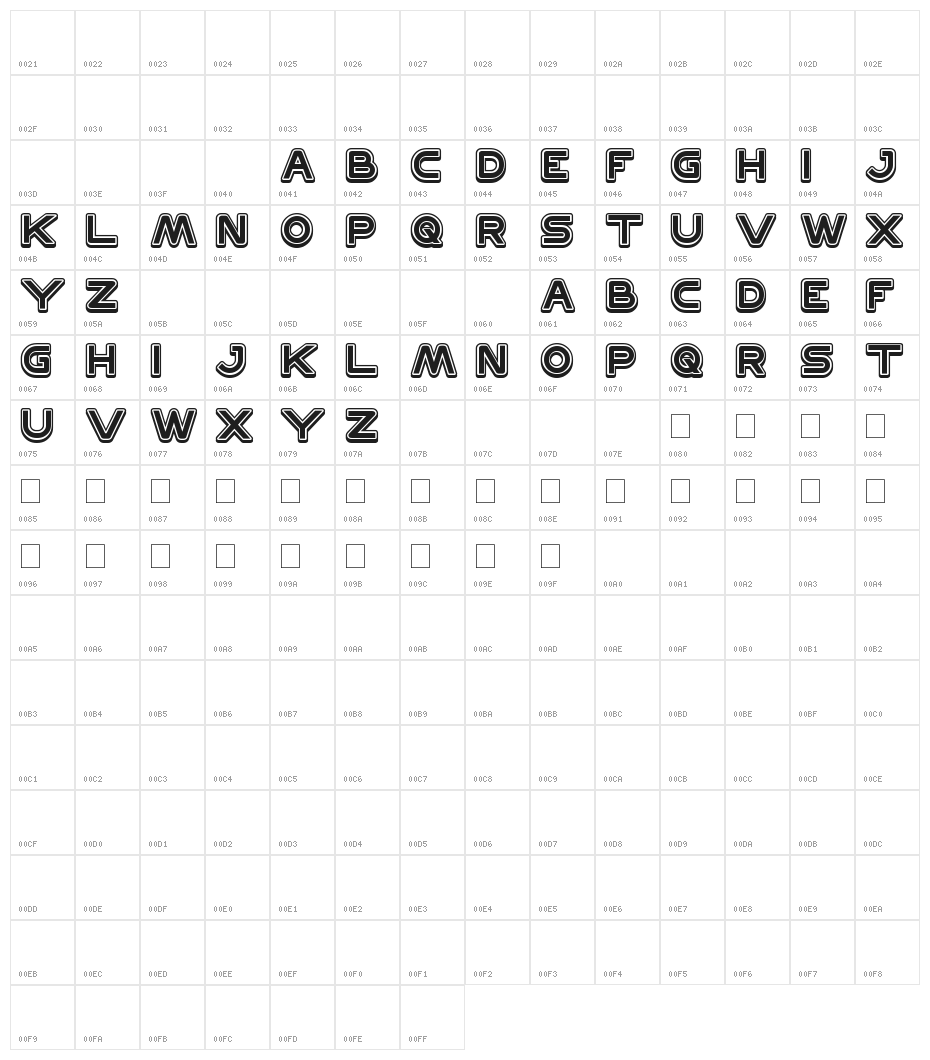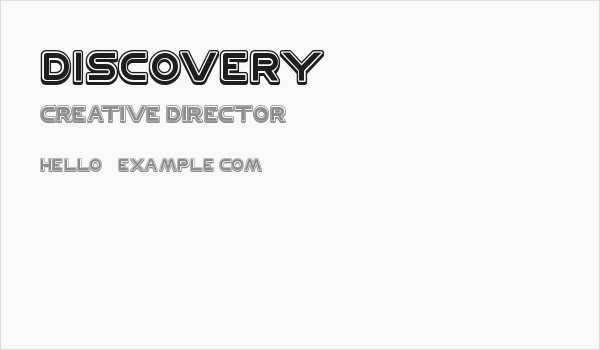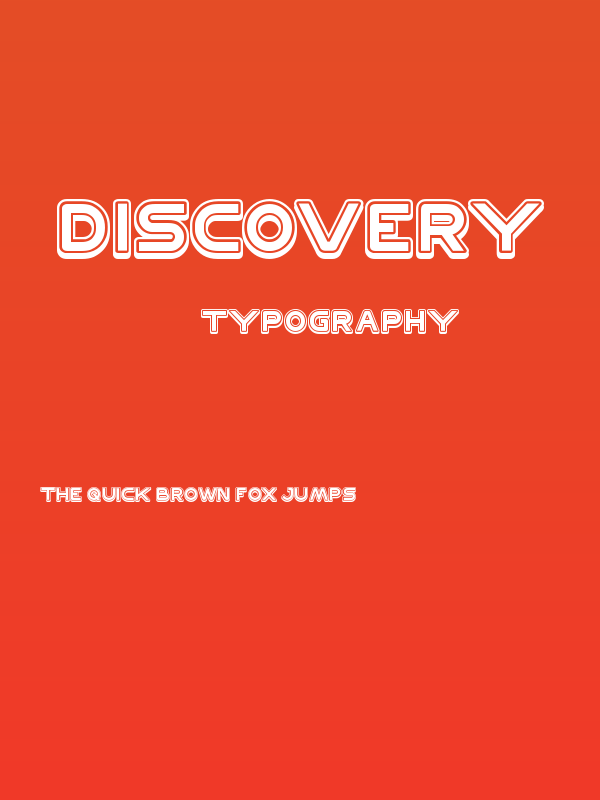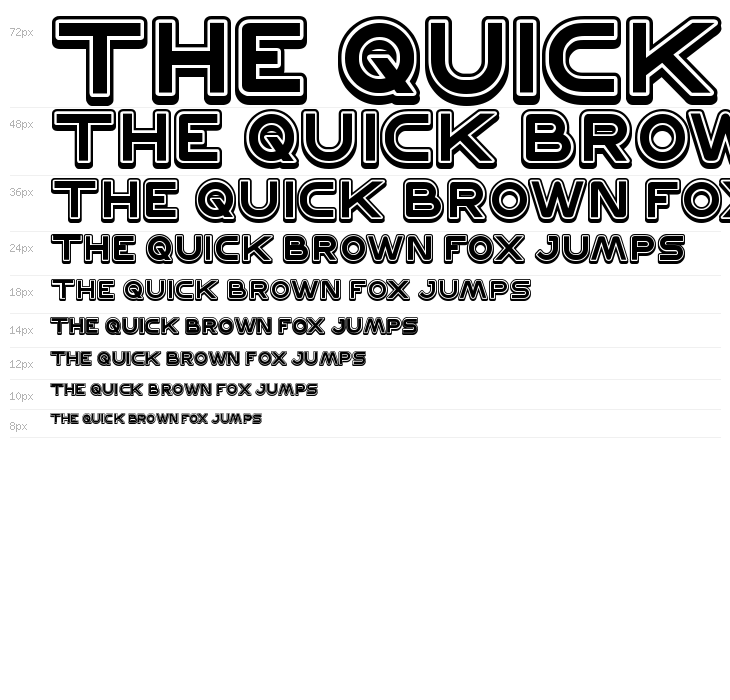
DISCOVERY Font
✎ Outline
| Kategorien | Outline |
| Gesamtstil | Modern, Retro |
| Vorgeschlagene Projekte | Ideal for branding, posters, headlines, and any project requiring a bold, eye-catching typeface. |